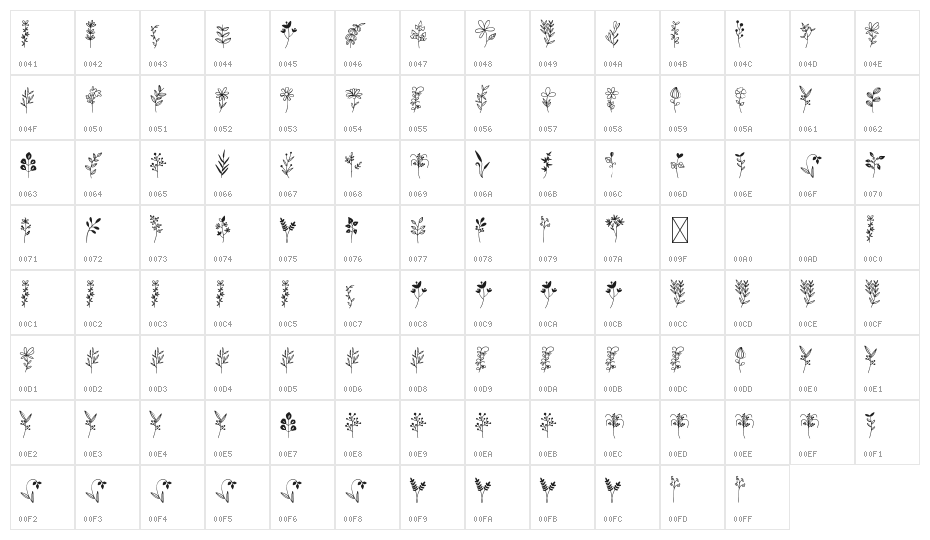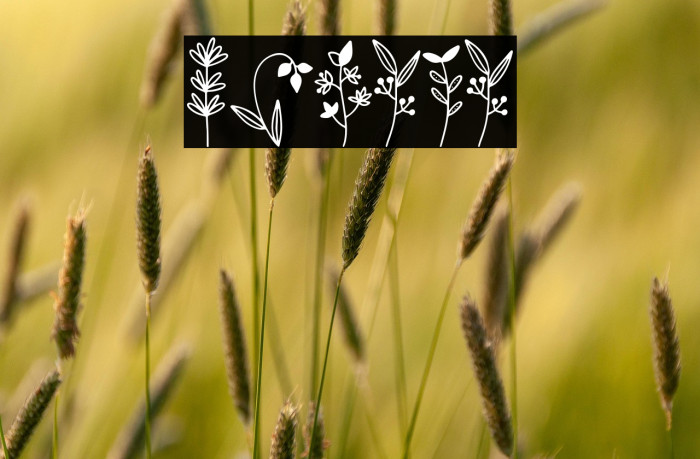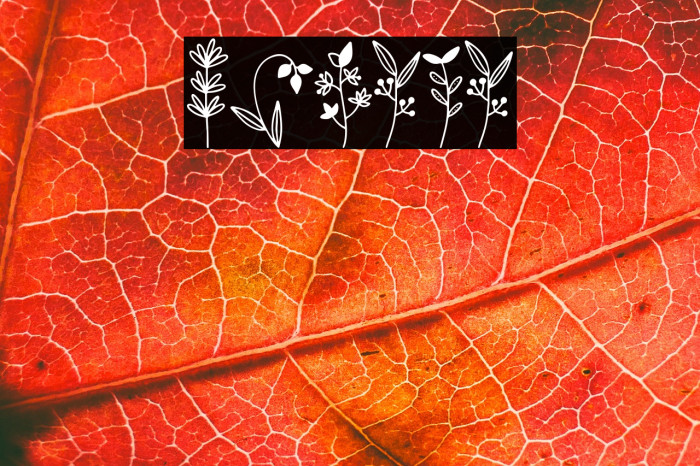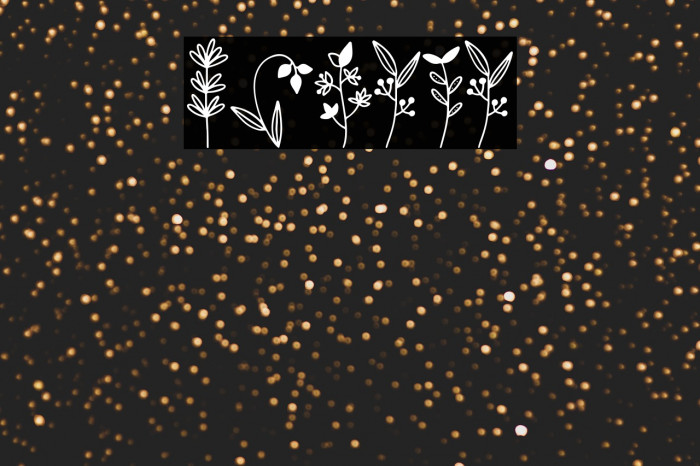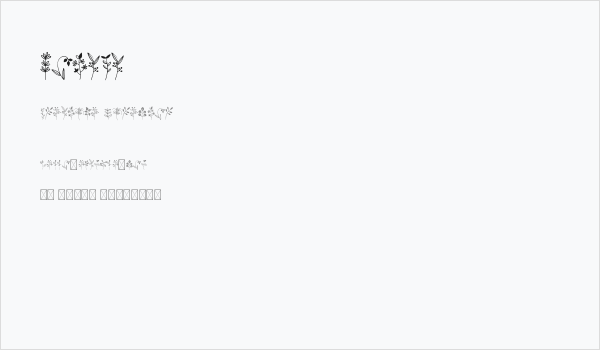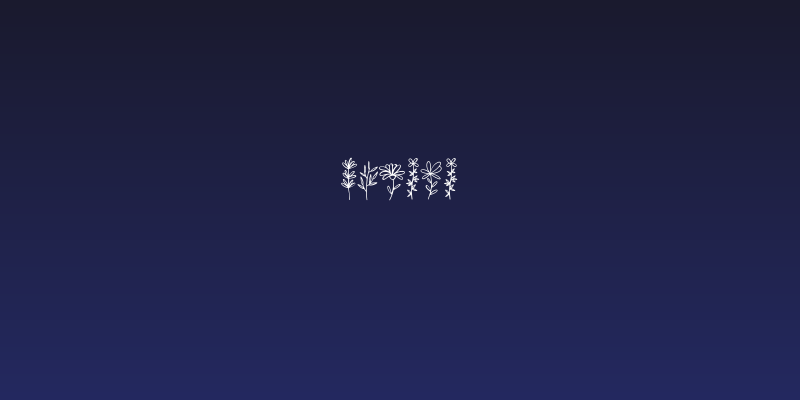
Botana Font
| समग्र शैली | Whimsical, Natural, Handcrafted |
| उपयोग का मामला | Decorative elements, Logos, Pattern design, Illustrations |
| सुझाए गए प्रोजेक्ट | Ideal for greeting cards, invitations, branding for eco-friendly or floral businesses, textile patterns, and decorative accents in print or digital media. |